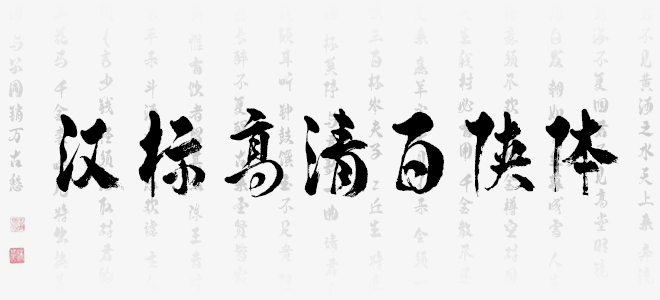
漢標(biāo)高清百俠體字體別具一格,大膽運(yùn)用弧度筆畫,充滿詼諧幽默的趣味。書法家對該字用筆大膽有新意,既有傳統(tǒng)書法筆畫的味道,又加入了作者對當(dāng)代藝術(shù)的理解。適用于文藝類的書刊、品牌廣告和產(chǎn)品包裝設(shè)計(jì),以及社交網(wǎng)絡(luò)的個(gè)性化用字。歡迎喜歡漢標(biāo)高清百俠體的朋友前來下載使用。
漢標(biāo)高清百俠體